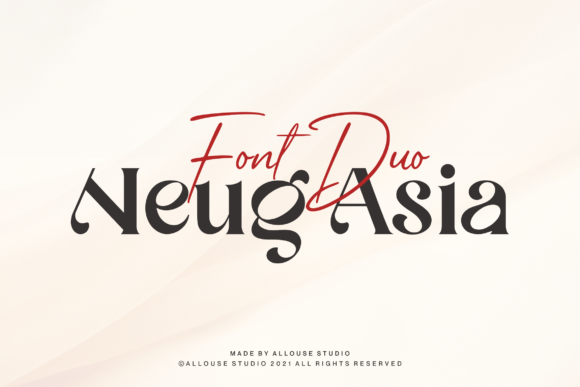
Neug Asia - это красивый и универсальный дуэтный шрифт (засечка и шрифт).
Мастерски разработанный, чтобы стать настоящим фаворитом, этот шрифт способен поднять каждую из ваших творческих идей на самый высокий уровень!